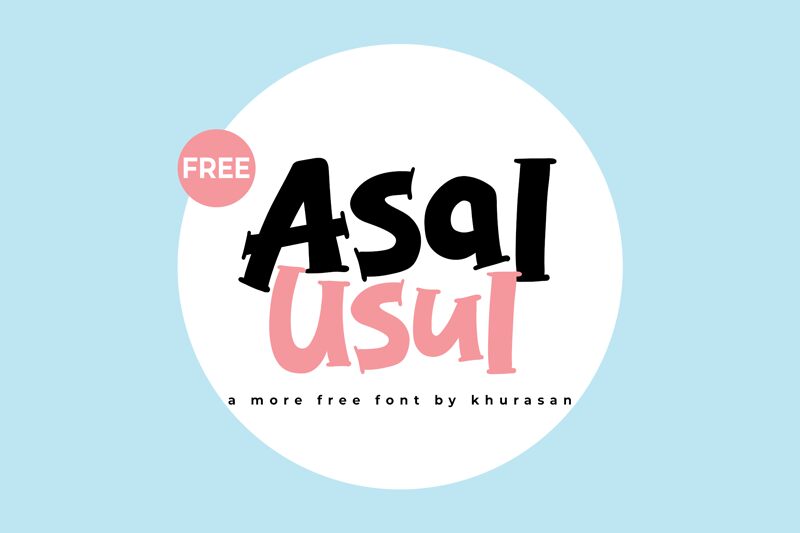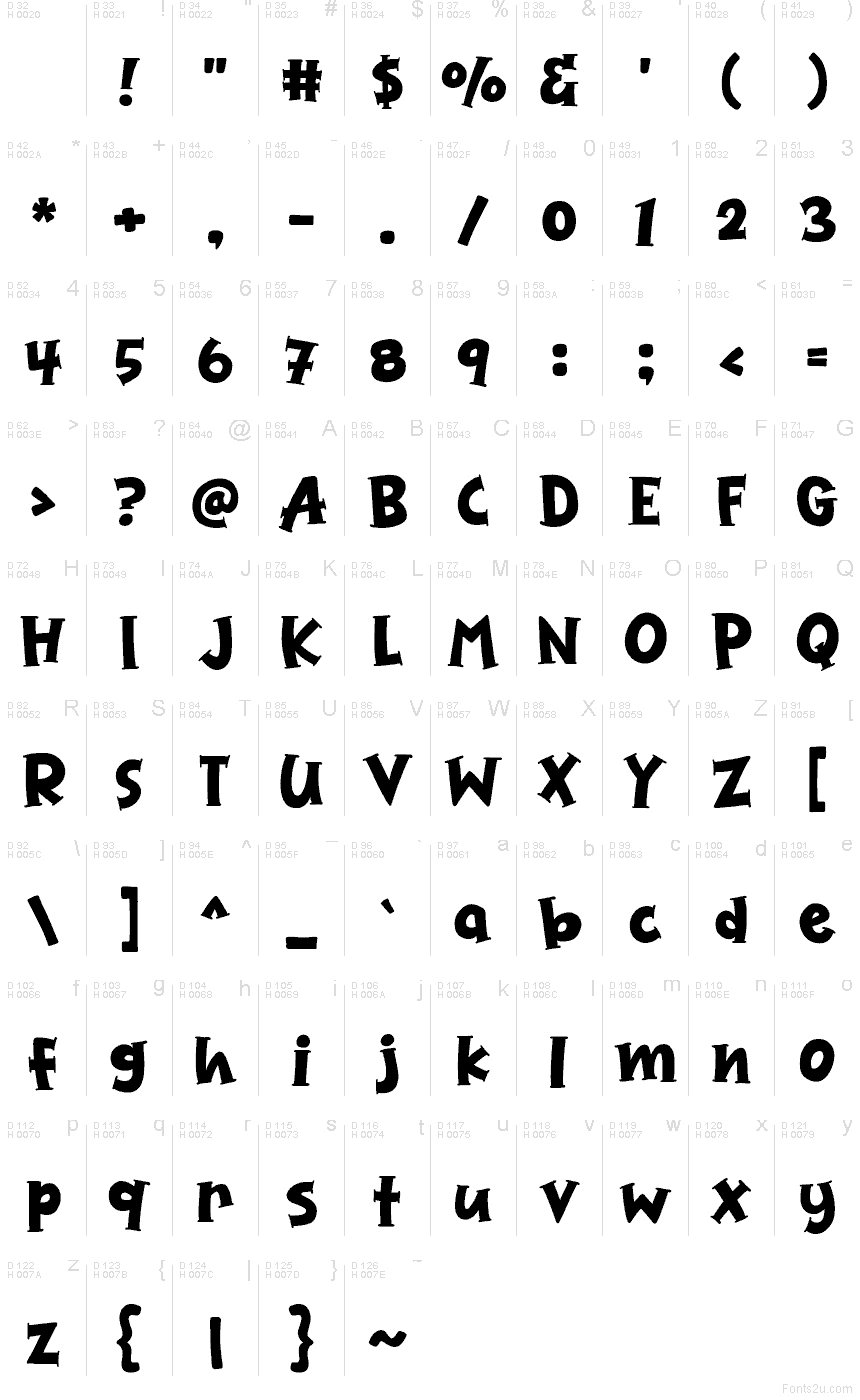
Asal Usul
Asal Usul di Khurasan è un font cartoon display gratuito con quell'attitudine da libro di storie disegnato a mano. Le lettere appaiono grandi, dinamiche e leggermente sbilenche, con tratti corposi, curve morbide e piccoli piedini squadrati che mantengono lo stile giocoso anziché levigato.
Funziona a meraviglia per copertine di libri per bambini, packaging di snack, branding in stile lavagna da bar, titoli di poster e allegre miniature YouTube, dove un font gratuito deve avere una voce amichevole e artigianale. Poiché le forme si inclinano e ondeggiano al punto giusto, è perfetto anche per loghi brevi, capilettera e volantini di eventi che cercano qualcosa di caloroso, audace e un po' birichino.